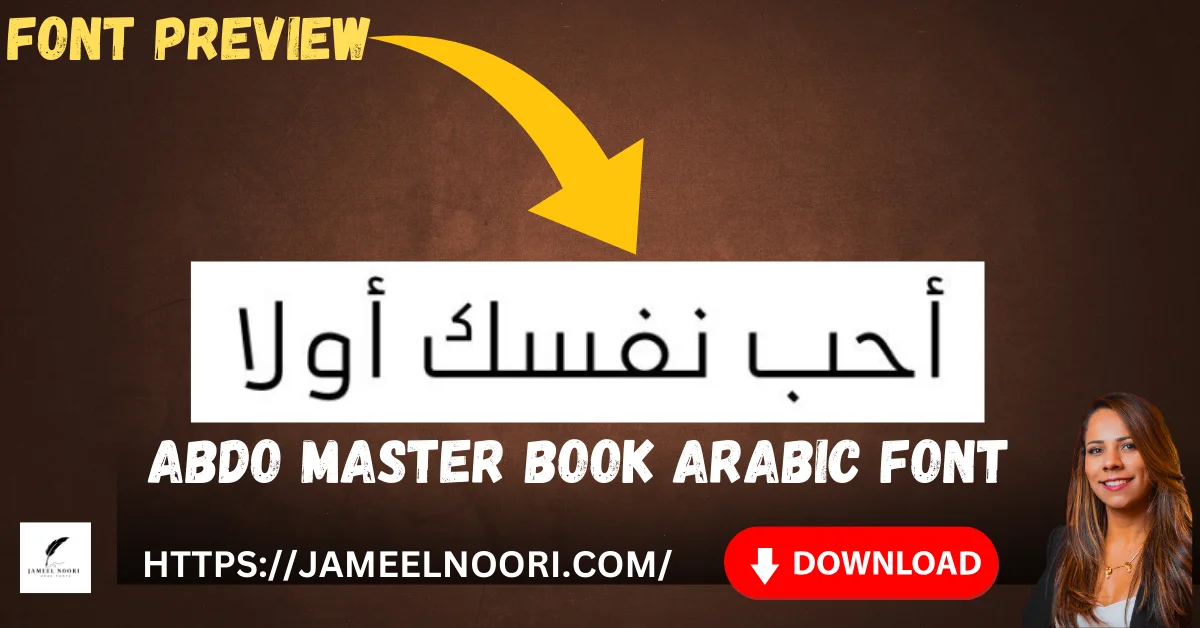
Abdo Master Book Arabic Font – Professional & Highly Readable Arabic Typeface for Designers & Users
Abdo Master Book Arabic Font aik professional aur highly readable Arabic typeface hai jo specially books, articles, Islamic content aur digital publishing ke liye design ki gayi hai. Ye font apni clean structure aur balanced letter spacing ki wajah se worldwide users ke darmiyan bohat popular hai. Arabic aur Urdu typography me interest rakhne walay log isay daily use ke liye prefer karte hain.
Key Features of Abdo Master Book Arabic Font
Abdo Master Book Arabic Font ki kuch important features neeche bullet points me di ja rahi hain:
• Clean aur readable Arabic typography
• Books aur long paragraphs ke liye best
• Professional Arabic calligraphy style
Ye features isay best Arabic font ki category me shamil karte hain, specially educational aur religious content ke liye.
What is Abdo Master Book Arabic Font?
Abdo Master Book Arabic Font aik TrueType Font (TTF) hai jo Arabic calligraphy ke traditional touch ko modern readability ke sath combine karta hai. Ye font long text reading ke liye perfect hai, khas taur par books aur PDFs ke liye.
Is font ka character structure smooth aur professional hai jo screen aur print dono par equally acha lagta hai. Is liye ye font designers, bloggers aur publishers ke liye aik expert choice mana jata hai.
Best Uses of Abdo Master Book TTF Arabic Font
Abdo Master Book Arabic Font ka use multiple purposes ke liye kiya ja sakta hai:
• Islamic books aur PDFs
• Urdu aur Arabic fonts based blogs
• Educational material
• Website content
• Mobile applications
Agar aap professional aur readable Arabic content banana chahte hain to ye font aik ultimate choice hai.
Abdo Master Book Arabic Font Character Map and Calligraphy Style
Character map of Abdo Master Book Arabic Font highlighting its smooth Arabic calligraphy and balanced letter design.
Character Map and Calligraphy Style
Abdo Master Book Arabic Font ka Character Map is baat ko clearly show karta hai ke is font ki calligraphy kitni balanced aur refined hai. Har letter ka shape clear hai jo reading experience ko improve karta hai.
Arabic fonts me character consistency bohat zaroori hoti hai aur ye font is requirement ko perfectly fulfill karta hai. Isi wajah se ye font Pakistan, Lahore, Karachi aur international level par use ho raha hai.
Why Designers Prefer Abdo Master Book Arabic Font
Designers Abdo Master Book Arabic Font ko is liye prefer karte hain kyun ke ye visually appealing hone ke sath readability ko compromise nahi karta. Ye font especially long text ke liye design kiya gaya hai.
Pakistan ke designers, khas taur par Lahore aur Karachi me, is font ko publishing aur digital projects me use karte hain. Ye font beginners aur experts dono ke liye equally useful hai.
Comparison with Other Arabic Fonts
Abdo Master Book Arabic Font ko jab doosray Arabic fonts se compare kiya jata hai to ye readability aur professional look me clearly lead karta hai.
FeatureAbdo Master BookOther Arabic Fonts
ReadabilityHighMedium
Book UseExcellentLimited
Rating4.4/5Average
Professional LookYesDepends
Agar aap aik reliable, professional aur easy-to-read Arabic font search kar rahe hain to Abdo Master Book Arabic Font aik perfect solution hai. Is ki popularity, high rating aur clean typography is baat ka proof hai ke ye font long-term use ke liye ideal hai.
Chahe aap Pakistan me hon ya kisi aur country me, ye font har user ke liye equally beneficial hai. Educational aur digital content ke liye ye font ek smart aur affordable choice hai.
Why is this font popular among designers?
Because of its readability and professional look.
Is this font suitable for Islamic content?
Yes, it is widely used for Islamic and educational material.